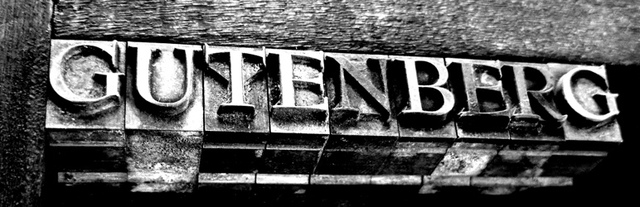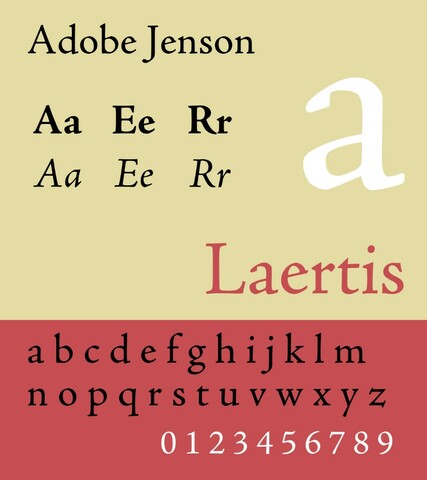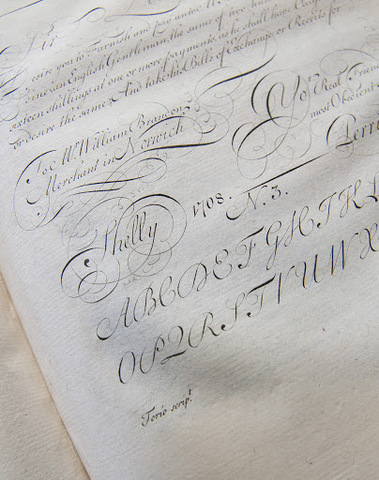
En el siglo II a. C., en Mesopotamia, se utilizaron punzones y troqueles para estampar formas de letras o glifos en sellos. Era una forma muy temprana de impresión. También hay evidencia de que se usaron técnicas de "impresión" similares en Babilonia, Creta y la Antigua Grecia.
En 1470 en Venecia, Nicolas Jenson diseñó un tipo de letra altamente legible inspirado en los estilos de letras romanas antiguas. Jenson es uno de los primeros tipos de letra Old Style o estilo antiguo, que se caracterizan por el poco contraste entre trazos gruesos y finos.
En 1528 los tipógrafos también estaban empezando a explorar formas de ahorrar espacio en los diseños. Los libros y otros materiales impresos aún no eran muy baratos de producir, por lo que los diseñadores se concentraron en comprimir el tracking (espacio entre caracteres) y el leading (espacio entre líneas). Esta necesidad de ahorrar espacio también llevó al desarrollo de la cursiva.
En el siglo XII, las letras manuscritas eran una forma de arte increíblemente hermosa en Europa, practicada por monjes que creaban manuscritos iluminados cubiertos con diseños de letras ornamentadas. El estilo de escritura perfeccionado por estos monjes se conoce ahora como gótico o caligrafía gótica.
A pesar de su negrura, las letras góticas nunca fueron el tipo de letra más fácil de leer, así que fue un alivio cuando los estilos tipográficos romanos se popularizaron en los siglos XV y XVI. -
En siglo XVIII, la Era de la Ilustración llegó con una avalancha de cambios para el mundo tipográfico. En Francia, la familia Didot diseñó una de las primeras fuentes serif modernas, que se caracterizaba por sus remates muy finos y un gran contraste entre los trazos gruesos y delgados.
El tipógrafo italiano Giambattista Bodoni desarrolló tipos de letras que también pueden clasificarse como fuentes modernas. -
Esta fue la era de las letras serif humanistas. Todo comenzó con William Caslon, un diseñador tipográfico de Londres, que creó una versión más refinada de las serif antiguas desarrolladas por Jenson algunos siglos antes.
Caslon es un tipo de letra romántico e innegablemente hermoso, que hace que todos los documentos impresos de este período se vean excepcionalmente elegantes. -
La tipografía sufrió un enfoque desordenado durante esta época. Las letras se reducían o estiraban para ajustarlas a los materiales publicitarios, como carteles y periódicos. Se utilizó una mezcla ecléctica de estilos para adaptarse a cada espacio disponible, lo que resultó en una apariencia excéntrica que abarcó desde un estilo inspirado en el circo hasta los estilos "vintage" que son tan populares en los cafés de moda actuales.
Con la invención de las computadoras en el siglo XX, las fuentes (versiones digitales de los tipos de letra) se convirtieron en la nueva moneda de la tipografía. A pesar de las emocionantes posibilidades que la revolución digital encerraba para los tipos de letras, la tipografía como disciplina pareció un poco fuera de lugar por un tiempo. Esto se debía a las limitaciones de la tecnología empleada en las pantallas, muchas fuentes se representaron como Tipo píxel rudimentario.